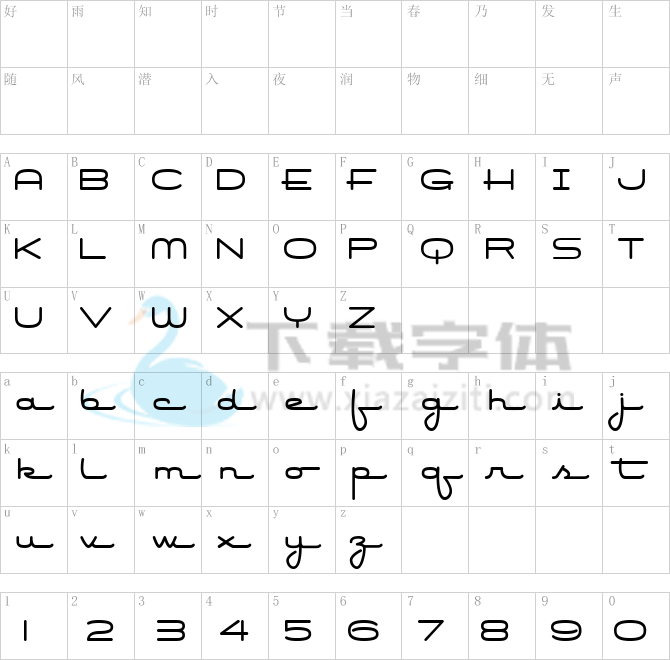
Air Conditioner.ttf字体下载,这款字体结构工整、笔画清晰,兼顾美观与易读性,适用于标题、正文、海报、包装、LOGO 等多种场景。字形优雅稳定,风格百搭耐看,适配日常排版与创意设计,让文字呈现更舒适、更具质感。Air Conditioner.ttf字体下载一笔一画,皆是细节,以均衡的比例、流畅的线条打造舒适视觉体验,字形端正大气,风格简约现代。无论是商业设计、品牌宣传还是日常排版,都能轻松驾驭,让文字更有格调与力量。Air Conditioner.ttf字体下载字体下载。